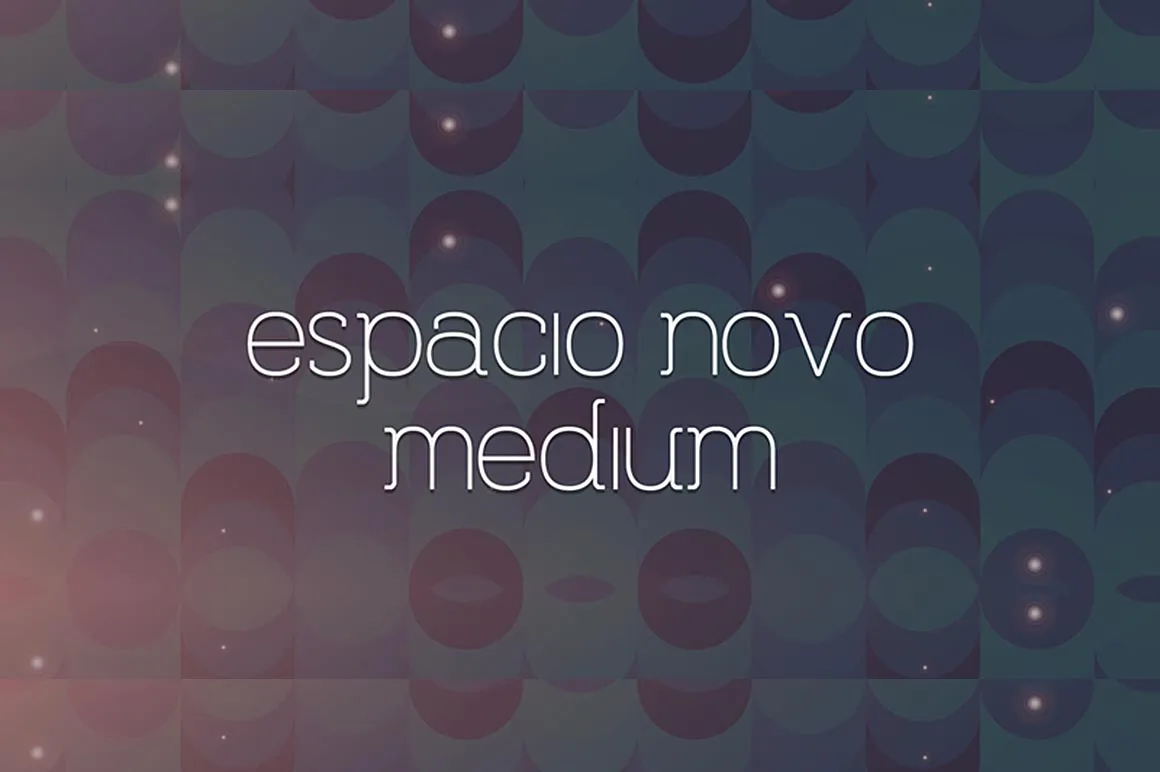
Espacio Novo Medium Font – Download Grátis
A Espacio Novo Medium é uma fonte moderna em estilo Blackletter, desenvolvida pelo talentoso designer Hamilton. Perfeita para qualquer projeto criativo que você esteja planejando, a Espacio Novo Medium oferece um toque elegante e único que tornará seu design distintivo e impecável. Esta fonte é perfeitamente adaptada para gráficos como letras de título ou banners, proporcionando uma experiência visual única e chamativa. Sua estética moderna, ao mesmo tempo clássica e sofisticada, a torna um recurso indispensável no seu arsenal de ferramentas design. A Espacio Novo Medium é mais do que apenas uma fonte – ela é uma peça chave para qualquer projeto de design que deseja chamar a atenção.